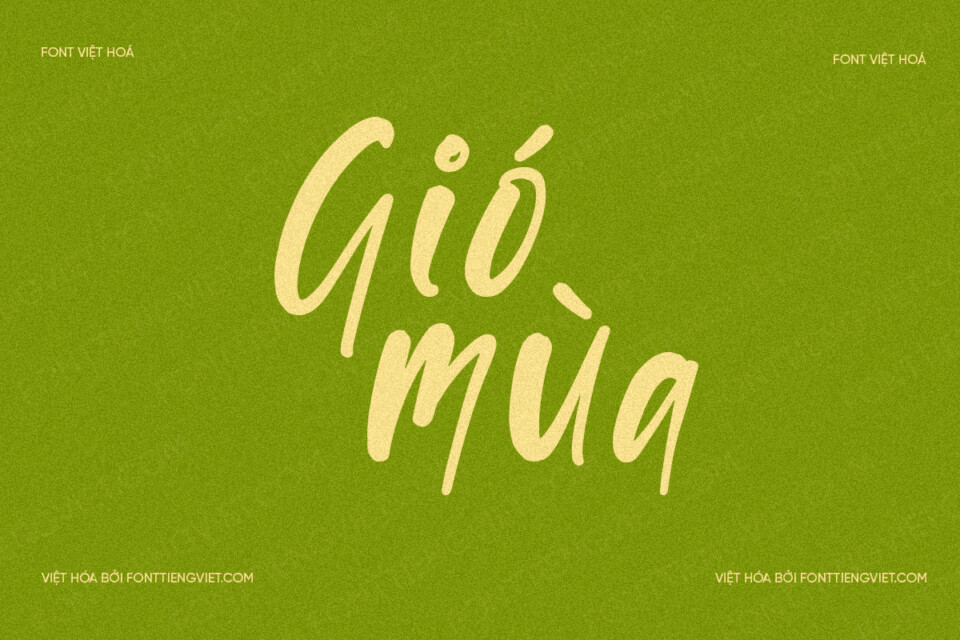
Tên font: Font Việt hóa VIP Scartoon
Tác giả: Letterena Studios
VIP Scartoon Việt hóa là một font chữ viết tay (script font) nổi bật với thiết kế mập mạp, tròn trịa và đầy đặn, mang đến vẻ ngoài vui tươi, dễ thương và cực kỳ thân thiện. Font này gợi cảm giác như những nét chữ được viết bởi trẻ con, hồn nhiên và ngộ nghĩnh, lý tưởng để tạo điểm nhấn độc đáo và thu hút mọi ánh nhìn trong các thiết kế đòi hỏi sự đáng yêu và gần gũi.
Với đặc điểm là hình dáng tròn mềm mại, nét viết tay to lớn và tính thẩm mỹ cao, VIP Scartoon là lựa chọn hoàn hảo cho các thiết kế muốn truyền tải sự trẻ trung, dễ thương và sự gần gũi, đặc biệt là trong lĩnh vực thiết kế áo: